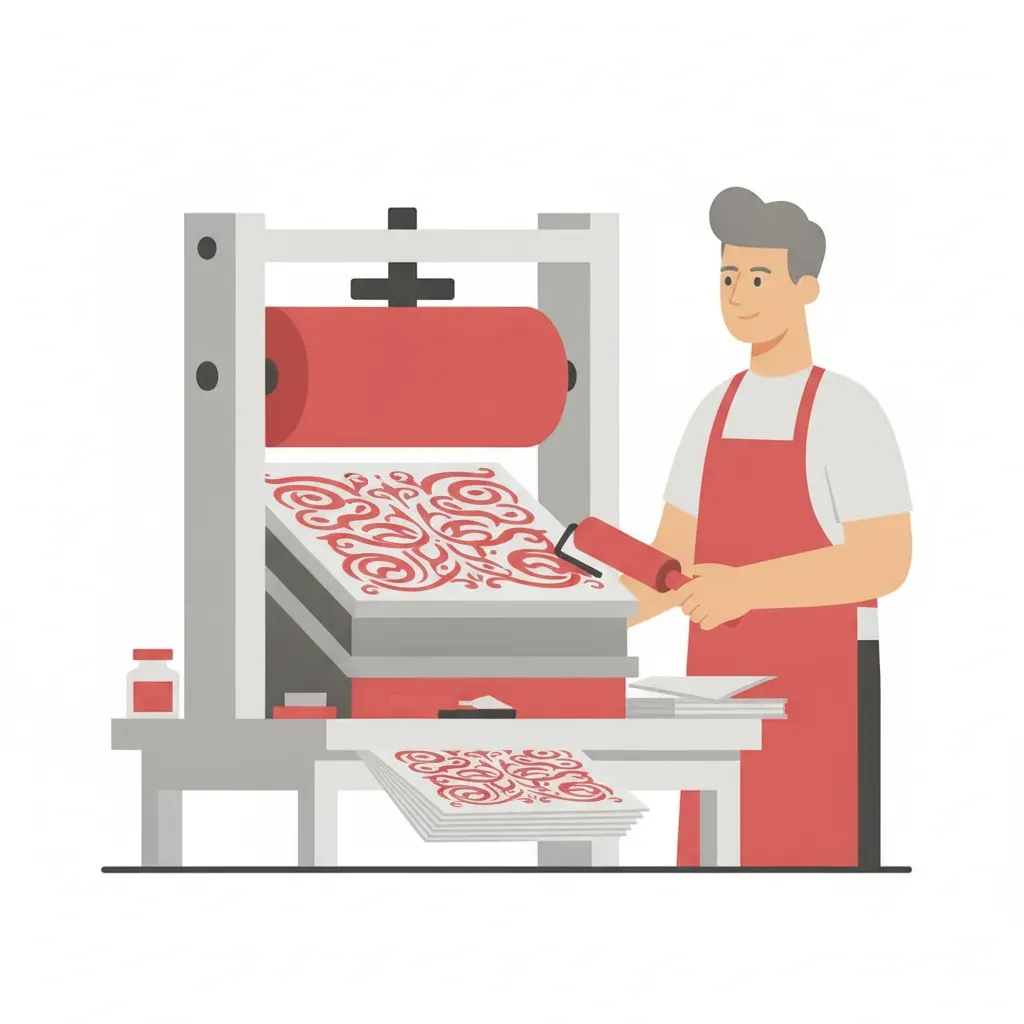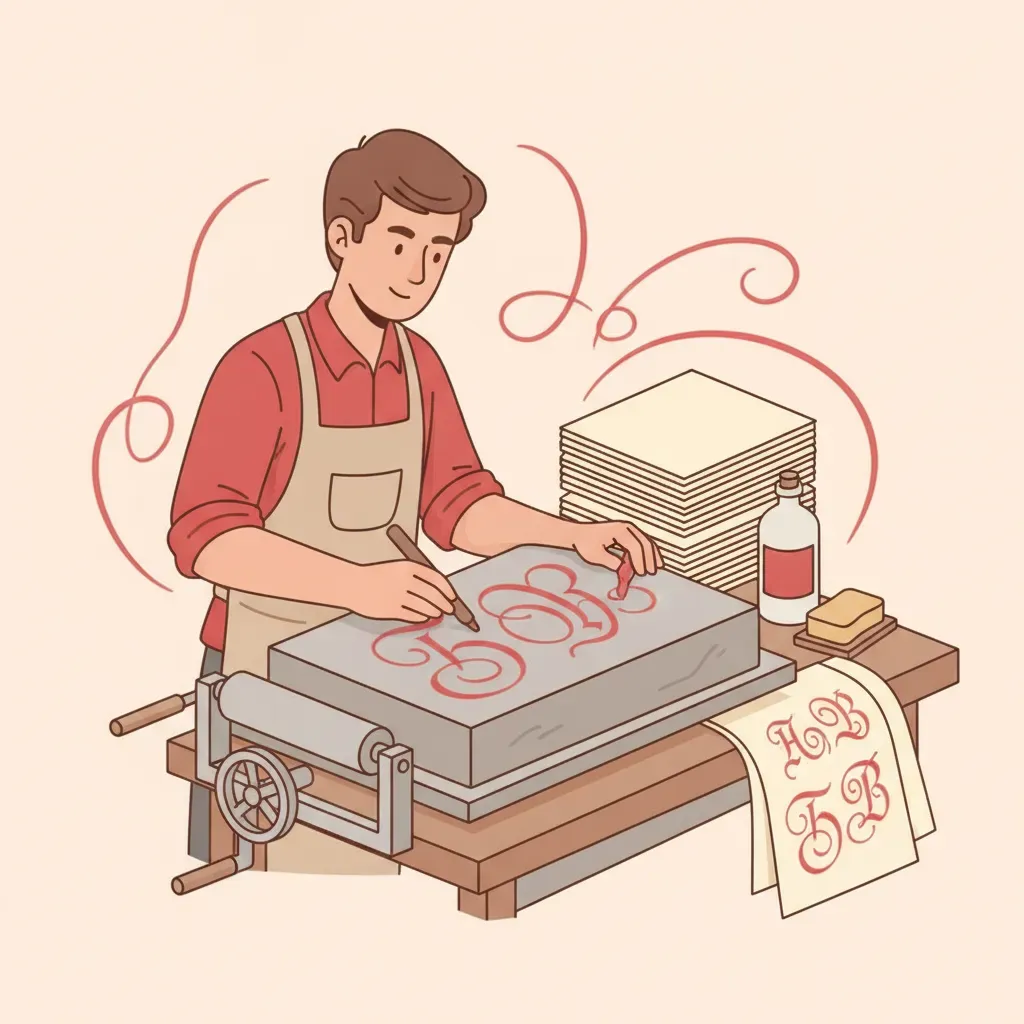
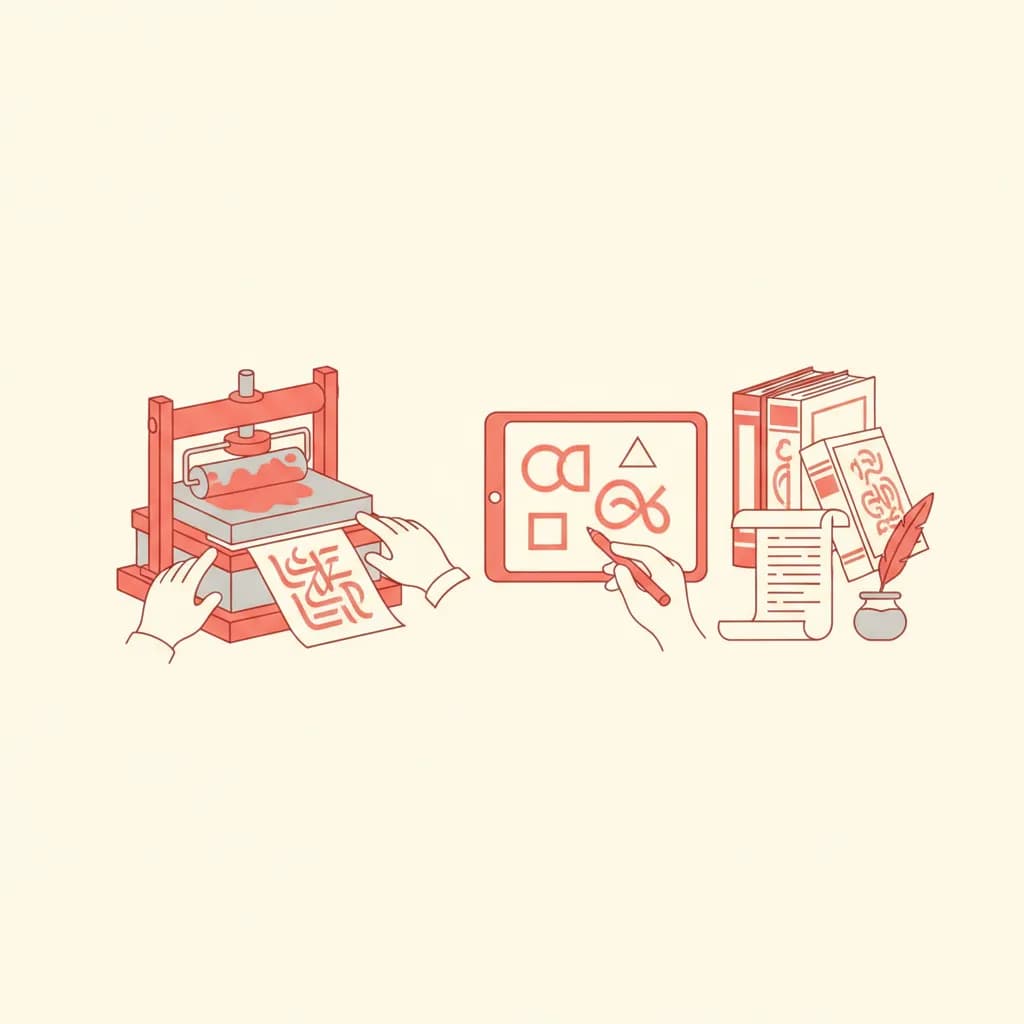
בשנת 1796 המציא האמן הגרמני אלויס זנפלדר שיטת הדפסה שתשנה את פני העולם. הליטוגרפיה – שמשמעותה המילולית "הדפס אבן" (מהמילים היווניות "ליטו" ו"גרפיה") – הייתה הרבה יותר מטכניקה חדשה: היא הפכה למנוע שהניע את ייצור הספרים, העיתונים, ובעיקר את עיצוב האותיות העבריות. ההיסטוריה של הטיפוגרפיה העברית המודרנית אינה מובנת כראוי ללא הבנת תפקידה המרכזי של הליטוגרפיה בעיצוב הגופנים שאנחנו משתמשים בהם יום-יום.
טכניקת ההדפס אבן אפשרה לראשונה הדפסה מדויקת של אותיות עבריות בקנה מידה גדול, בדיוק גרפי שלא היה אפשרי בשיטות קודמות. בתי דפוס בווילנה, ורשה, ואודסה אימצו את הטכנולוגיה החדשה, ובתהליך זה נוצרו אבות הטיפוס של הגופנים העבריים שממשיכים לחיות בעולם הדיגיטלי של ימינו.
ליטוגרפיה עברית – ההיסטוריה שעיצבה את הפונטים שאנחנו מכירים
הדפס האבן פועל על עיקרון פיזיקלי פשוט: שמן ומים אינם מתערבבים. הסופר או האמן כתב על אבן גיר מיוחדת בדיו שמנית. לאחר מכן הורטבה האבן במים, וכאשר הורח עליה דיו להדפסה, הוא נדבק אך ורק לאזורים השמניים – כלומר לאותיות עצמן. הנייר הונח על האבן ונלחץ בלחץ אחיד, והדפוס הועבר בשלמותו.
היתרון הגדול של שיטה זו לעומת הדפוס המסורתי בתבליטי עץ או מתכת היה הדיוק הגרפי. ניתן היה לייצר קווים דקים, עיגולים מושלמים, ווים עדינים – כל המאפיינים שהופכים את האות העברית לאלגנטית. הדפסת אבן אפשרה לסופרים ולאמנים לשמר את כל הניואנסים הקליגרפיים של כתב היד שלהם, ולהעבירם לדפוס המוני.
עבור הטיפוגרפיה העברית, פירוש הדבר היה מהפכה. האות העברית, עם גגותיה האופקיים, תגיה, ריבועיותה המיוחדת וקווי העובי המשתנים שלה, הייתה קשה מאוד לחיתוך בעץ או ביציקה במתכת. הליטוגרפיה ביטלה את הבעיה הזו כמעט לחלוטין.
בין השנים 1820 ל-1900 פרחו בתי דפוס ליטוגרפיים ביידישלנד – אותה רצועה של ערים יהודיות גדולות שנמתחה מוורשה ועד אודסה. כל בית דפוס פיתח "כתב יד" ייחודי לאותיות שלו, שנבע מהקליגרפים שהועסקו שם ומהטעם האסתטי של הבעלים.
שלושה סגנונות עיקריים התגבשו בתקופה זו:
מעצבים גרפיים שמבינים את ההיסטוריה הליטוגרפית של הגופן העברי מסוגלים לקבל החלטות טיפוגרפיות מושכלות יותר. הנה כמה עקרונות מעשיים שנובעים ישירות מהמסורת הזו:
שלב 1: זיהוי הניגודיות בגופן
גופנים עבריים שמקורם בסגנון הרבני-ליטוגרפי מאופיינים בניגודיות גבוהה בין קו עבה לדק. לפרויקטים יוקרתיים ורשמיים – כמו הזמנות חתונה או מיתוג עסקי – גופנים עם ניגודיות כזו מעבירים אוטוריטה ואלגנטיות. לפרויקטים שמבקשים נגישות ומודרניות, גופנים בעלי ניגודיות נמוכה יותר (המושפעים מהסגנון המעוגל) יתאימו טוב יותר.
שלב 2: קריאת "הגג" של האות
אחד המאפיינים הבולטים שהליטוגרפיה שימרה הוא "הגג" האופקי של האות העברית – הקו העליון שמחבר בין האותיות. גופנים שמכבדים את הגג ומשמרים אותו עקבי ברוחב ובעובי ישמרו על קריאות טובה גם בגדלים קטנים. כדאי לבדוק את הגג בגדלי 10-12 פוינט לפני בחירת גופן לגוף טקסט.
שלב 3: בחירת גופן לפי הקשר היסטורי
כשמעצבים חומרים שמדברים על מסורת, שורשים או זהות ישראלית – גופן שמחזיר לאסתטיקה הליטוגרפית יוצר תהודה רגשית עמוקה יותר. לדוגמה, לפרויקטים עם אופי היסטורי-לאומי, פונט מגילת העצמאות שעוצב בהשראת הקליגרפיה של אותה תקופה, מביא את המסורת הזו לחיים בצורה עכשווית.
שלב 4: שילוב גופנים מסורתיים עם מודרניים
גישה מוצלחת היא לשלב גופן עברי בעל מאפיינים ליטוגרפיים קלאסיים בכותרות, לצד גופן סנס-סריף נקי בגוף הטקסט. השילוב יוצר מתח יצירתי בין עבר לעתיד, ומעשיר את חוויית הקריאה. על התאמת פונטים ניתן לקרוא בהרחבה ולמצוא דוגמאות קונקרטיות לשילובים כאלה.
נקודת מפתח:
מעצבים רבים מושפעים מהאסתטיקה הליטוגרפית מבלי להבין את המגבלות הטכניות שלה. הנה הטעויות הנפוצות ביותר:
טעות 1: שימוש בגופן ליטוגרפי-קלאסי בגדלים קטנים מדי
הגופנים שנוצרו בהשראת הדפוס הליטוגרפי מאופיינים בקווים דקים מאוד בחלק מהאותיות. כאשר מדפיסים אותם בגדל קטן מ-10 פוינט, הקווים הדקים עלולים להיעלם לחלוטין, ולפגוע קשות בקריאות. תמיד יש לבדוק את הגופן בגדל הסופי שבו ייעשה שימוש בפועל.
טעות 2: ערבוב לא מכוון של שני סגנונות ליטוגרפיים שונים
מעצבים שאינם מכירים את ההיסטוריה עלולים לשלב גופן ברוח הסגנון הרבני-קלאסי עם גופן בסגנון המעוגל-פולני, ולקבל תוצאה שנראית חסרת עקביות. כל גופן עברי נושא DNA ויזואלי ממקורו הליטוגרפי, ושילוב של שני DNA-ים מנוגדים יוצר "רעש" אסתטי.
טעות 3: שימוש בגופן רטרו-ליטוגרפי לפרויקט שדורש נגישות
כאשר מעצבים מחפשים "נוסטלגיה" ובוחרים גופן עם אופי ליטוגרפי מובהק לאתר אינטרנט, הם לעיתים מתעלמים מדרישות נגישות. גופנים עם ניגודיות גבוהה מאוד עשויים להיות קשים לקריאה עבור אנשים עם לקויות ראייה מסוימות. יש לוודא תמיד שיחס הניגודיות בין הטקסט לרקע עומד בתקן WCAG 2.1.
טעות 4: התעלמות מרווח השורות בגופנים ליטוגרפיים
בתי הדפוס הליטוגרפיים עיצבו גופנים לדפוס על נייר פיזי, עם מאפייני רווח ספציפיים. בהעברה לדיגיטל, גופנים אלה דורשים לעיתים קרובות התאמת line-height לערך של 1.6-1.8 – גדול יותר מהברירת המחדל – כדי לשמר את הנשימה הנכונה בין השורות.
המעבר מליטוגרפיה לדפוס מכני ולאחר מכן לדיגיטל לא מחה את המורשת הגרפית של בתי הדפוס הגדולים. להפך – בכל שלב של הטכנולוגיה, מעצבים ביקשו לשמר את האסתטיקה שהציבור כבר הכיר ואהב. כפי שמתואר במאמר כשהאות הייתה כוח, לכתב היד ולמסורות הדפוס יש כוח עמוק בעיצוב הזהות הגרפית של תרבות.
בשנות ה-50 וה-60 של המאה ה-20, כאשר חברת Linotype ואחרות ביקשו לדיגיטז גופנים עבריים, הן פנו לארכיוני בתי הדפוס הליטוגרפיים הגדולים ושחזרו את הגופנים הקלאסיים בפורמטים חדשים. כך הגיעו אלינו גופנים כמו "פרנק-רול" ו"דוד" – שמקורם ישיר בסגנון הליטוגרפי של המאה ה-19.
עבור מעצבים גרפיים, ההבנה של המורשת הליטוגרפית מעשירה את יכולת קבלת ההחלטות הטיפוגרפיות. כשבוחרים גופן עברי לפרויקט, כדאי לשאול: מאיזה מסורת גרפית הוא בא? מה הניגודיות שלו מסמלת? האם הגג שלו מחבר אותנו למסורת הכתיבה הרבנית, או שמא הוא מנותק ממנה בכוונה? כל תשובה לשאלות אלה מוסיפה שכבת משמעות לעיצוב.